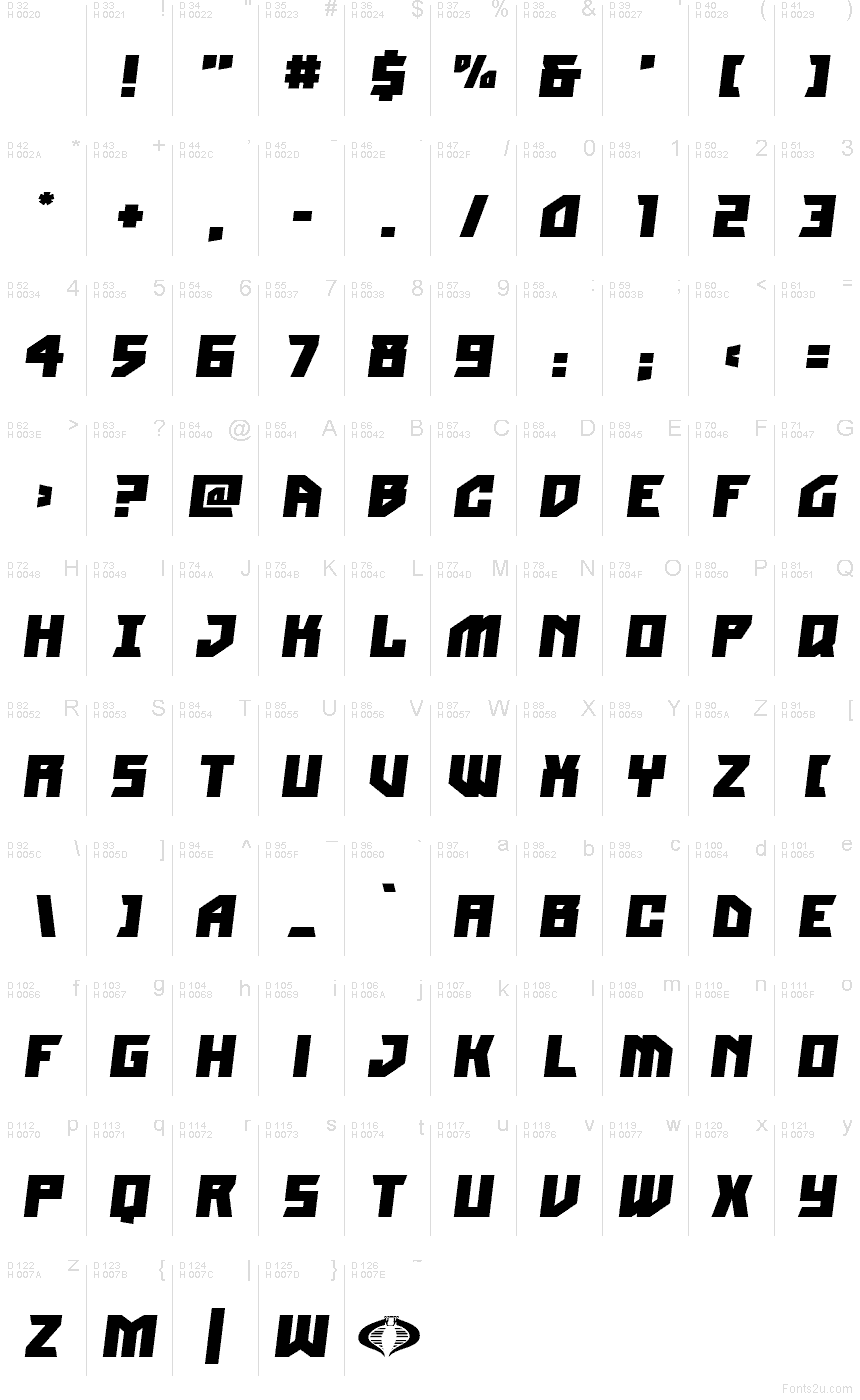
Omni-cobra Wide
Omni-cobra Wide de Iconian Fonts es una tipografía techno de exhibición gratuita con formas anchas e inclinadas y ángulos afilados que otorgan a cada letra un aspecto mecánico y tenso. Los caracteres se sienten comprimidos lateralmente, con secciones rectas interrumpidas por cortes diagonales y aperturas en bloque que mantienen el diseño activo en todo el texto.
Omni-cobra Wide funciona de maravilla para títulos de juegos, pósteres de ciencia ficción, logotipos arcade, gráficos de carreras, folletos de eventos y branding deportivo donde una línea angular fuerte es más efectiva que las curvas suaves. Esta tipografía gratuita también es ideal para pies de fotos, banners web, portadas de álbumes y gráficos de mercancía, ya que su geometría estirada transmite un ritmo futurista y rígido sin adornos innecesarios.